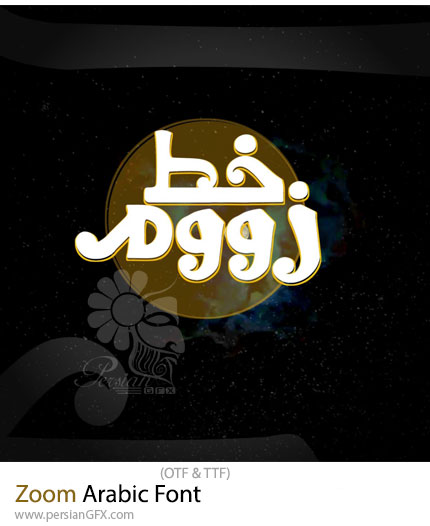
در این بخش شاهد فونت عربی به نام زووم می باشید که با فرمت های TTF و OTF بر روی سایت برای دانلود قرار گرفته است. فونت عربی زووم یکی از فونتهای جذاب و محبوب است که در طراحیهای گرافیکی و تایپوگرافیهای عربی کاربرد دارد. این فونت به دلیل ظاهری مدرن و خوانا، برای طراحیهای دیجیتال، تبلیغات، وبسایتها و حتی طرحهای چاپی بسیار مناسب است. فونت زووم معمولاً برای کاربردهای متنوعی از جمله طراحی لوگو، بنرهای تبلیغاتی، و حتی در طراحیهای مربوط به رسانههای اجتماعی استفاده میشود. فونت عربی زووم با طراحی مدرن، خوانایی بالا و تنوع وزنها یک انتخاب عالی برای پروژههای دیجیتال و گرافیکی است. این فونت نه تنها زیبایی و جذابیت را به طراحی شما اضافه میکند، بلکه با ویژگیهای فنی آن، مناسب استفاده در پروژههای مختلف آنلاین و چاپی میباشد.
ویژگیهای کلیدی فونت زووم:
- خوانایی بالا: فونت زووم طراحی شده تا در اندازههای کوچک و بزرگ به خوبی خوانا باشد. این ویژگی باعث میشود تا در وبسایتها یا تبلیغات آنلاین بهویژه در دستگاههای موبایل، به راحتی قابل خواندن باشد.
- ظاهر مدرن و شیک: این فونت ظاهری مدرن دارد و بهخوبی با طراحیهای معاصر همخوانی دارد. برای پروژههایی که به دنبال جلوهای حرفهای و شیک هستند، فونت زووم انتخاب مناسبی است.
- سازگاری با طراحیهای دیجیتال: فونت زووم بیشتر برای طراحیهای دیجیتال و آنلاین طراحی شده است و بهطور خاص برای محیطهای وب، اپلیکیشنها و پلتفرمهای آنلاین ایدهآل است.
- تنوع وزنها: این فونت معمولاً در چندین وزن مختلف (سبک، معمولی، بولد و غیره) ارائه میشود، که به طراحان این امکان را میدهد تا بسته به نیاز پروژه، از وزنهای مختلف استفاده کنند.
- حس حرکت و انرژی: فونت زووم معمولاً برای پروژههایی که نیاز به ایجاد حس حرکت و انرژی دارند، مناسب است. به همین دلیل، در طراحیهای پویا و متحرک یا در رسانههای اجتماعی که نیاز به جذب توجه سریع دارند، بسیار محبوب است.
کاربردها:
- طراحی وب و اپلیکیشن: فونت زووم بهویژه در طراحی وبسایتها و اپلیکیشنها که نیاز به فونتی خوانا و مدرن دارند، استفاده میشود.
- تبلیغات آنلاین: برای بنرهای تبلیغاتی، پستهای شبکههای اجتماعی و تبلیغات دیجیتال که به ظاهر شیک و جذاب نیاز دارند، این فونت گزینه خوبی است.
- طراحی لوگو: فونت زووم در طراحی لوگوهایی با ظاهر مدرن و حرفهای نیز کاربرد دارد.
- محتواهای ویدیویی و رسانهای: در ایجاد متنهای ویدیویی یا معرفیها، این فونت میتواند ظاهر جذابی داشته باشد.